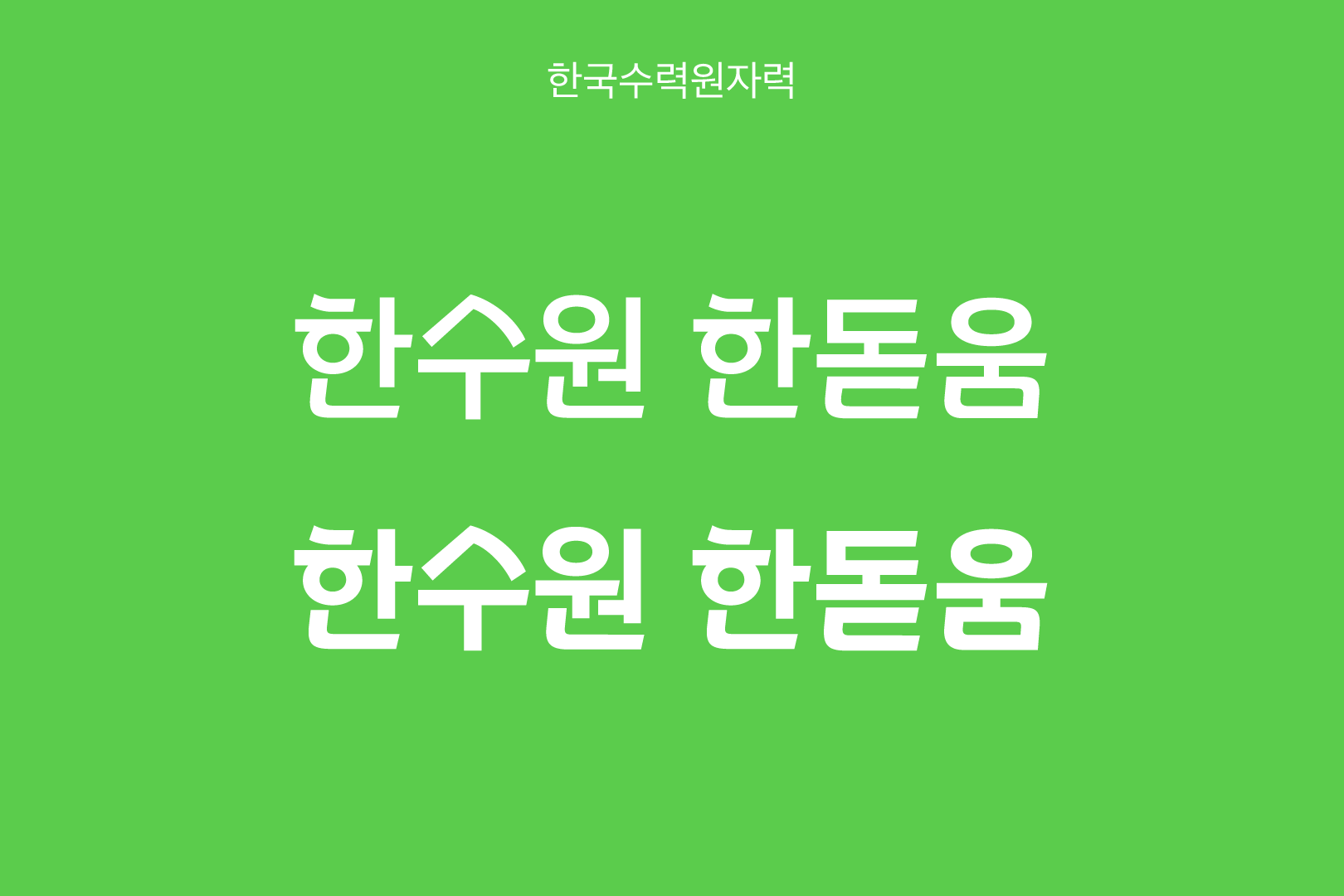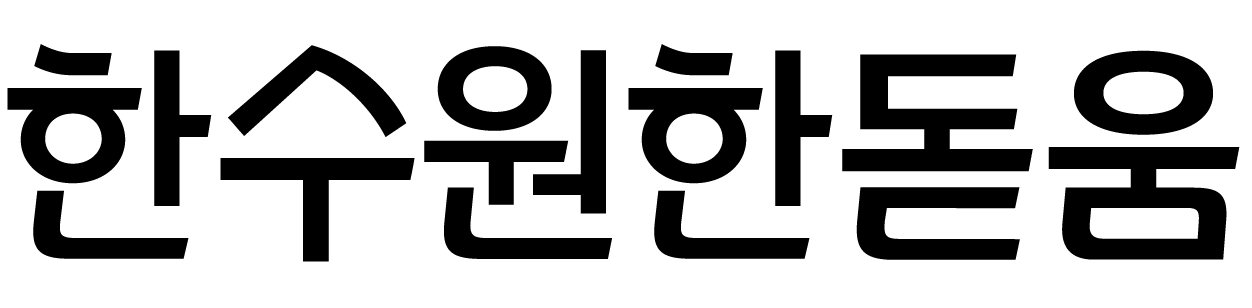
한수원 한돋움
한수원 서체는 에너지기업, 발전산업에 맞는 견고하고 안정감 있는 형태를 기본으로 국민과의 소통, 지역과의 조화의 의미를 유선형 포인트로 표현하였다. 한글 자소와 자소의 연결은 소통과 조직의 짜임새를 나타내면서 공공의 신뢰성을 상징한다.
• Sans,민부리